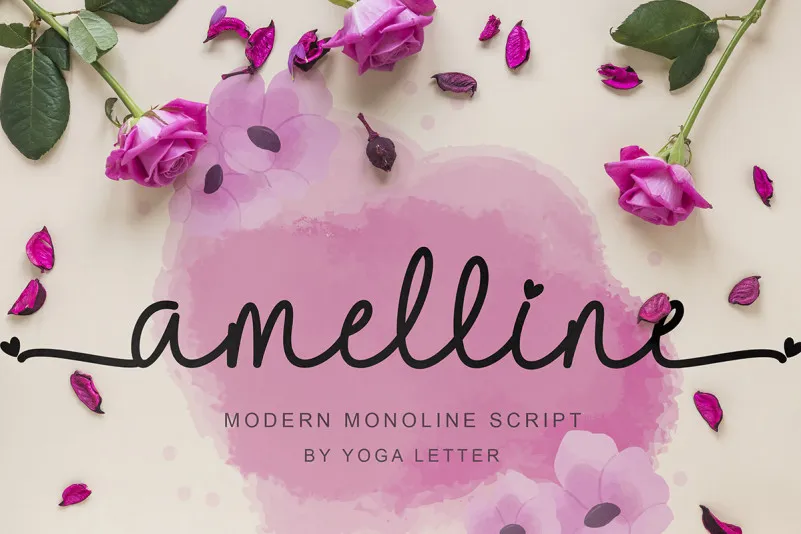
Amelline Font – Download Grátis
A fonte ‘Amelline Font’ da categoria Signature Fonts é perfeita para criar uma sensação elegante e moderna em seus projetos. Desenhada pelo designer Yoga Letter, esta fonte monocapa script é ideal para qualquer aplicação, desde convites de casamento até trabalhos profissionais. Seu design suave permite que você personalize suas criações sem comprometer a estética da fonte. Com um estilo moderno e clássico, ‘Amelline Font’ se destaca em diferentes ambientes. Suas ornamentações são tão fáceis de usar quanto seu design gráfico. Perfeito para ocasiões como festas de verão ou noivos casando durante o inverno, esta fonte também é uma excelente escolha para trabalhos que exigem um tom leve e descontraído. Adotar a ‘Amelline Font’ na sua próxima criação é uma maneira inteligente de garantir que seus materiais são elegantes e profissionais. Suas características suaves ajudam em qualquer projeto, seja para logomarcas, identidades corporativas, cartazes ou impressão digital. Além disso, a ‘Amelline Font’ também se destaca por ser uma fonte versátil, adaptável para diversos contextos de uso, garantindo que sua marca ou comunicação tenha sempre um tom atraente. O seu design único e elegante o torna um recurso ideal para os criadores de conteúdo, designers gráficos e profissionais do marketing digital.